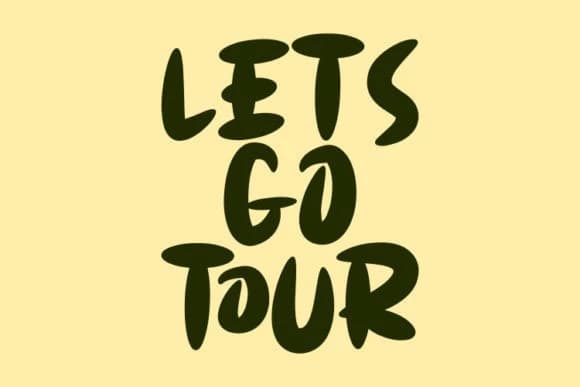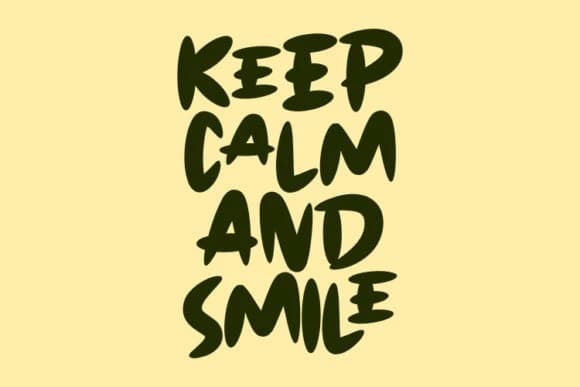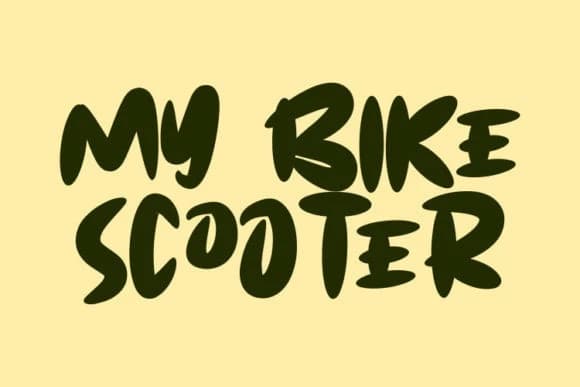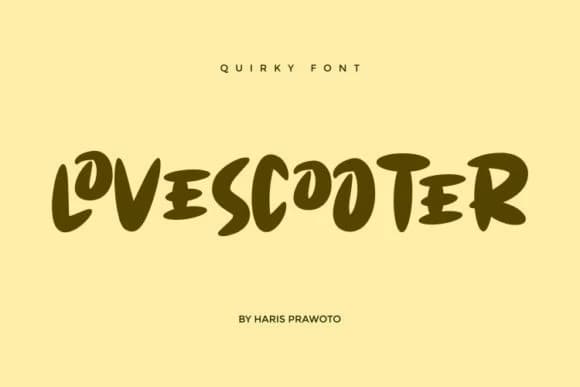
Lovescooter Display Font, kalın harfli ve tuhaf bir gösterim yazı tipidir. Dostane hissi sayesinde bu yazı tipi son derece çok yönlüdür ve geniş bir bağlam yelpazesine uyum sağlar. Yaratıcı fikirlerinizin içine ekleyin ve bunun onları nasıl öne çıkardığını görün!
Lovescooter Display Font, kalın harfli ve tuhaf bir gösterim yazı tipidir. Dostça bir hissi bu yazı tipini inanılmaz derecede çok yönlü kılıyor, geniş bir bağlam yelpazesine uyum sağlar. Yaratıcı fikirlerinize ekleyin ve bunun onları öne çıkardığını fark edin!